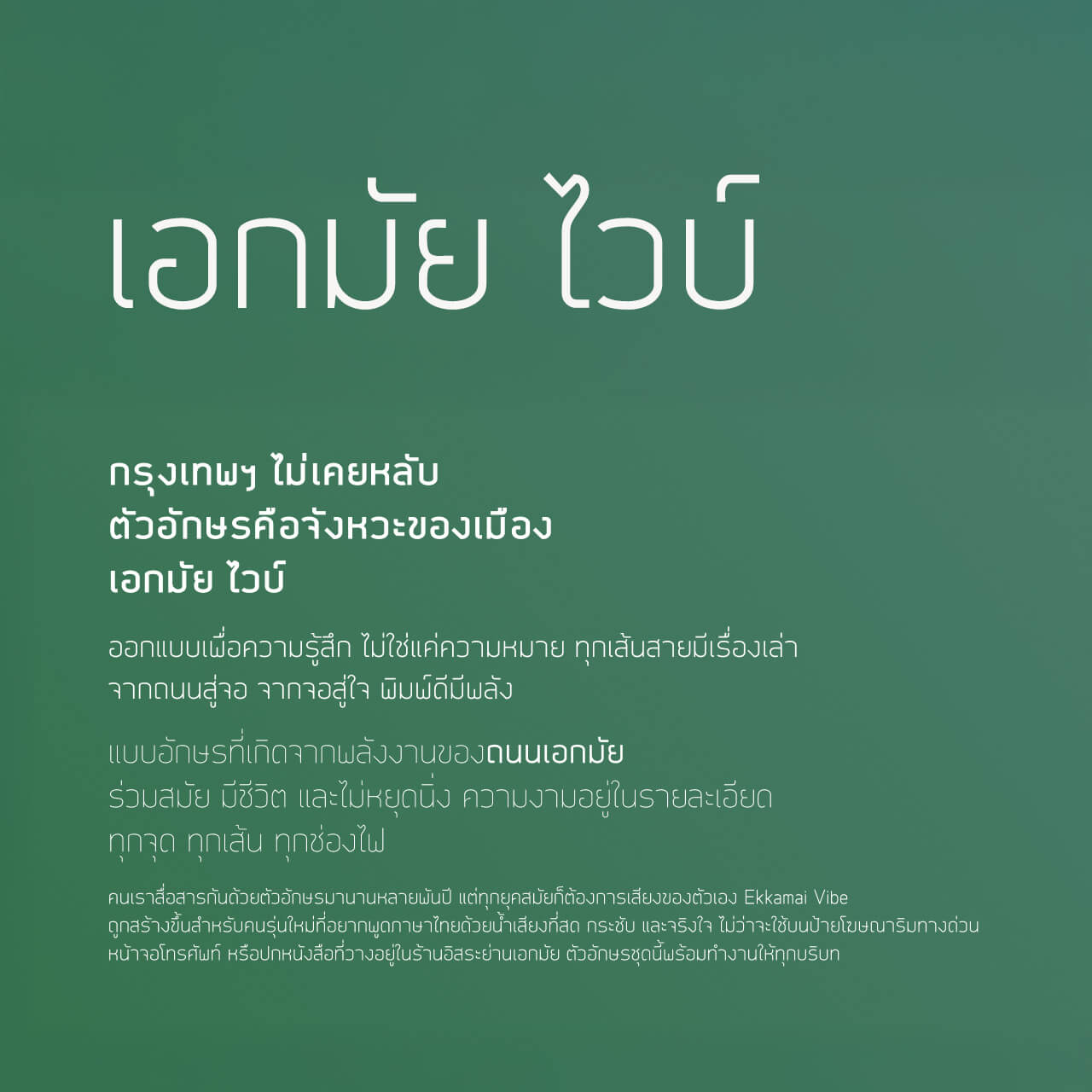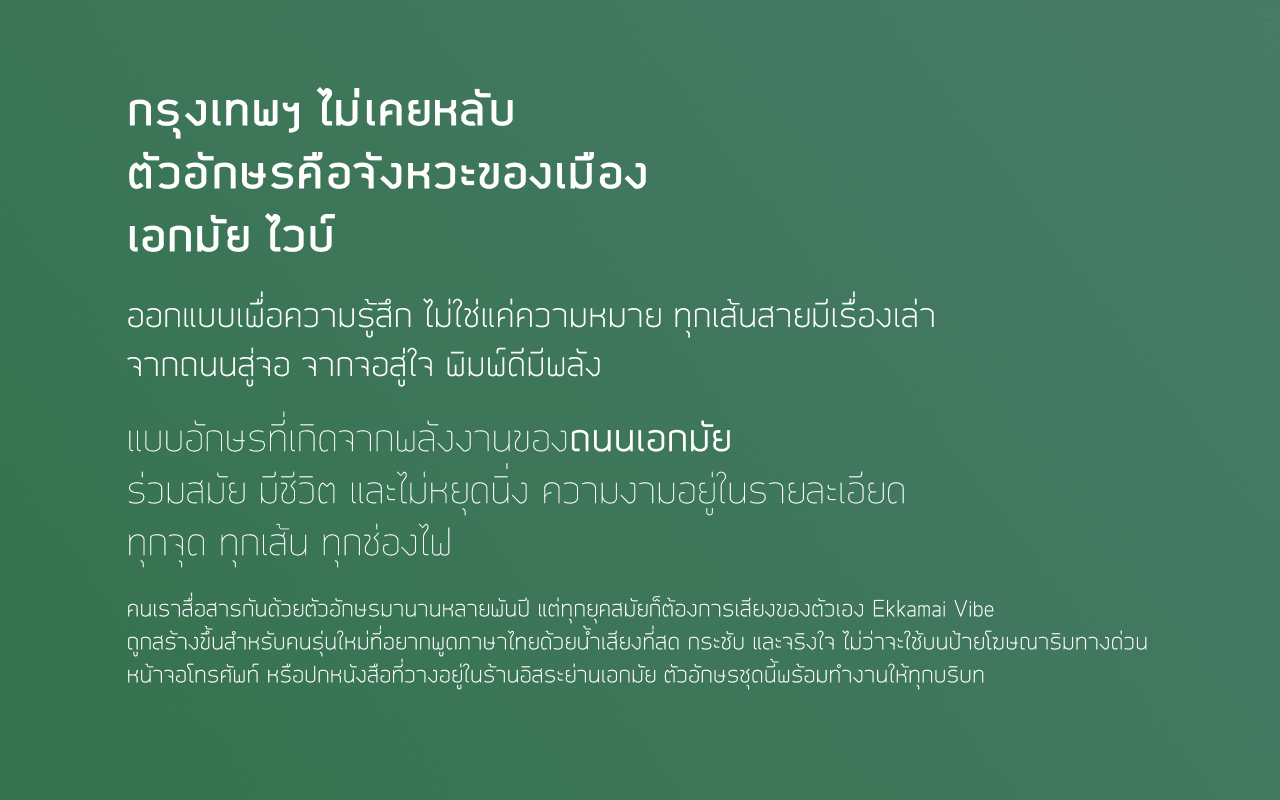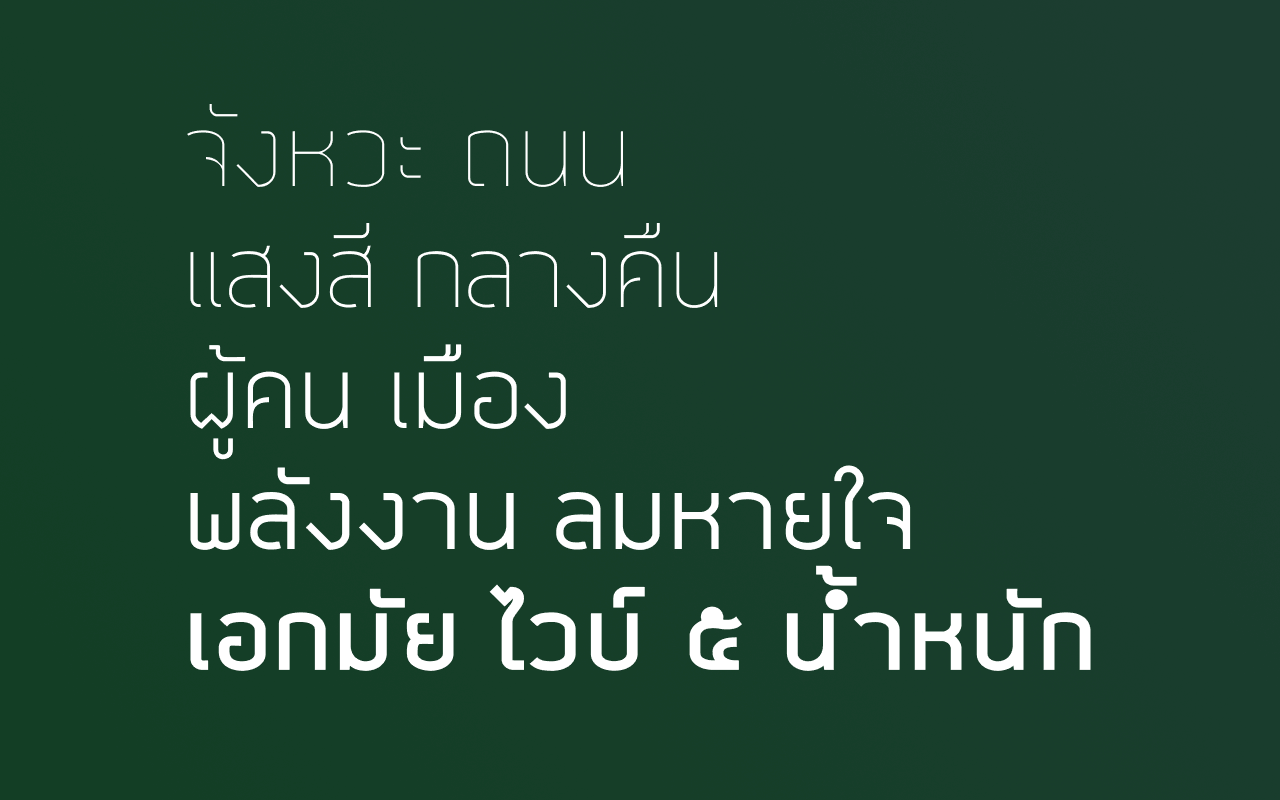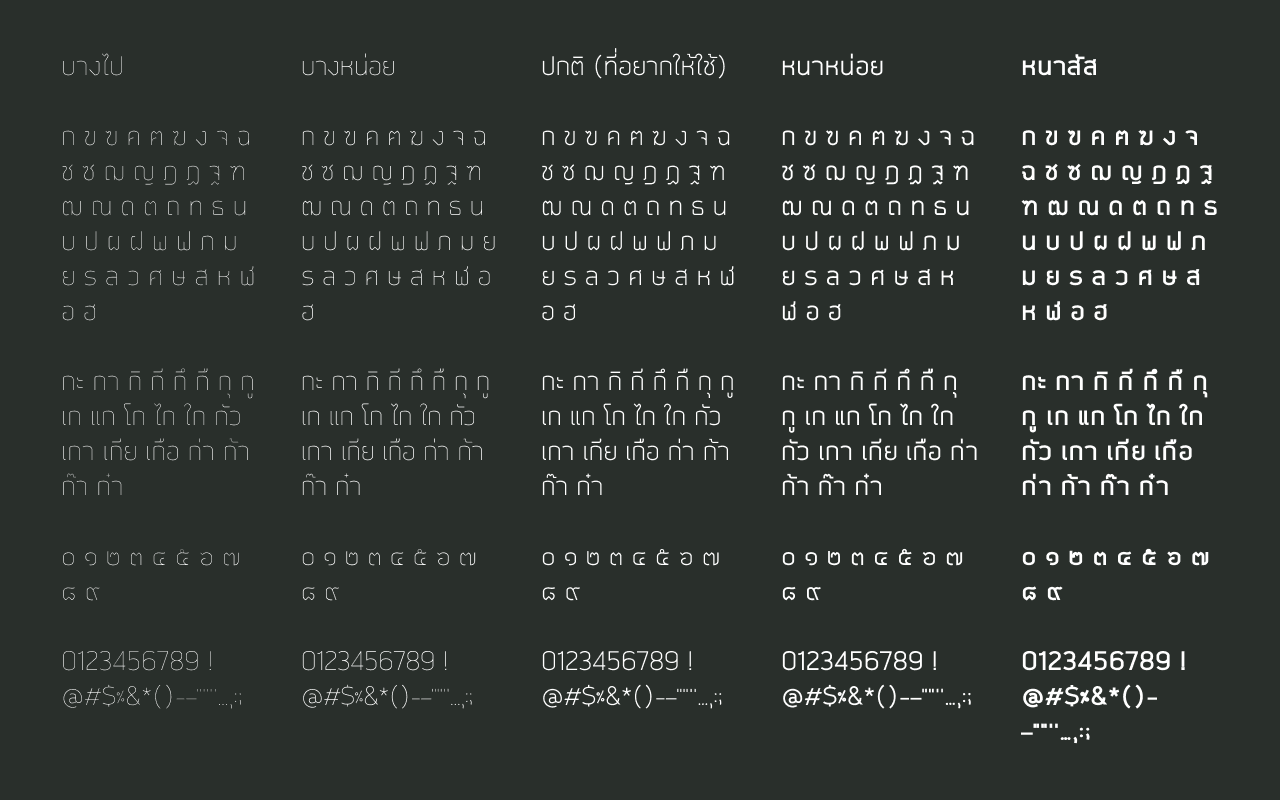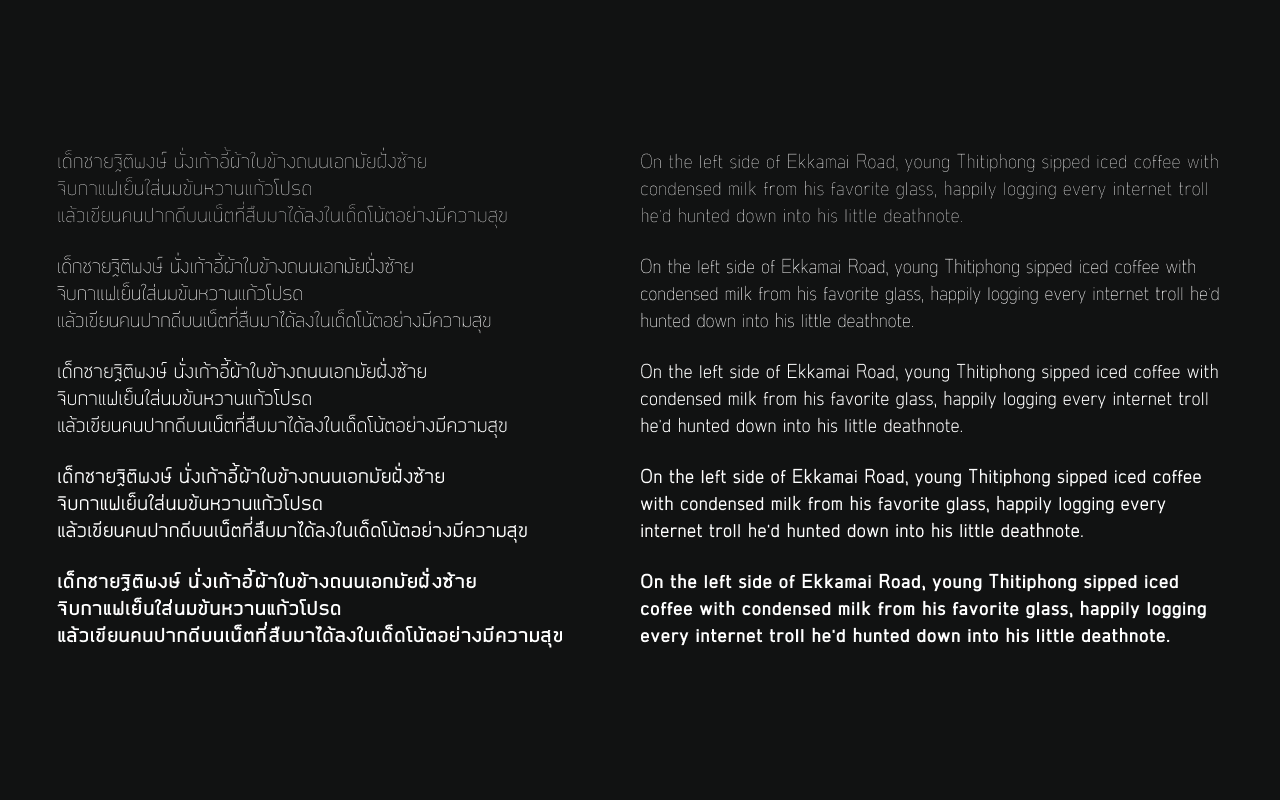
เอกมัย ไวบ์ (Ekkamai Vibe)
ภาคต่อของฟอนต์เอกมัย นิว ที่เงียบหายไปตั้งแต่ Fontlab 6 จนตอนนี้ Fontlab version 8 ออกหลายปี ที่สัญญาว่าจะปั่นฟอนต์ก็ไม่ได้ทำ เลยได้นำรากฐานจากเอกมัย นิว ที่มีแต่ก่อนแต่เดิมมาปรับแก้ แล้วเข็นแบบ 5 น้ำหนักออกมาจนได้เป็น ฟอนต์เอกมัย ไวบ์ ครับ
ที่ตั้งชื่อ vibe เพราะตัวนี้ทำขึ้นมาตามอารมณ์ เอาของเก่า บั๊ก และข้อเสนอแนะที่รวบรวมไว้มาปรับแก้อีกครัง และขยายจาก 3 น้ำหนักเป็น 5 น้ำหนัก